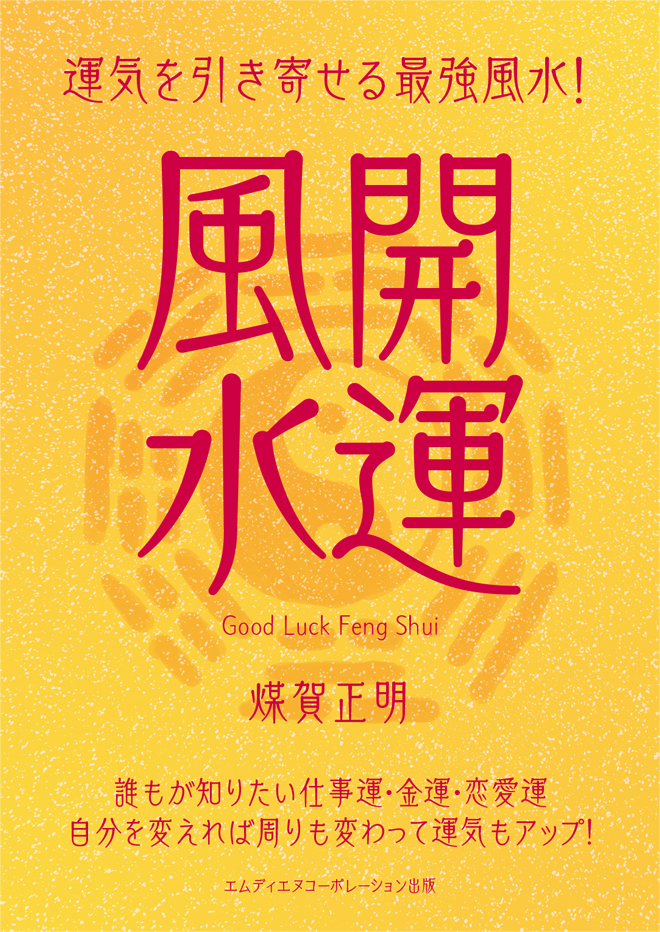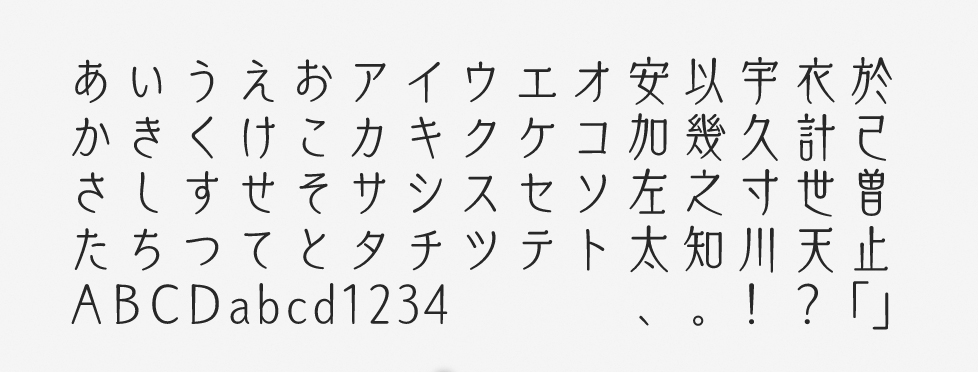
「オーブ」について
オーブは2018年に提供が開始された丸ゴシック体風のデザインフォントです。古代中国で青銅器の表面に刻まれていた「金文」にヒントを得て開発されました。伸びやかで優雅な佇まいで、どことなくレトロな雰囲気も漂っています。かな文字には優しい手書きのニュアンスが残されています。
「オーブ」の特徴
オーブは縦に細長い字面のフォントです。一般的に縦長のシルエットは上品さやスマートさを感じさせ、オーブを縦組みで使うとスッキリとした「細さ」のイメージは強調されます。同時に、通常より行送りがやや狭めでも窮屈な印象を与えません。
横組みでは、実際にはベタ組みでもアケ組みのような見え方になります。字幅に合わせた間隔で文字を並べたいときには、OpenTypeフォント機能のプロポーショナルメトリクスを適用すると良いでしょう。
オーブで組む文字の量については、作例のリードくらいの長さであればまったく問題なく使えます。小説や雑誌などではなく、特にマンガやアニメで面白い効果が得られるはずです。たとえば、マンガ内のキャラが読んでいる本文がオーブ、などの演出が面白いでしょう。